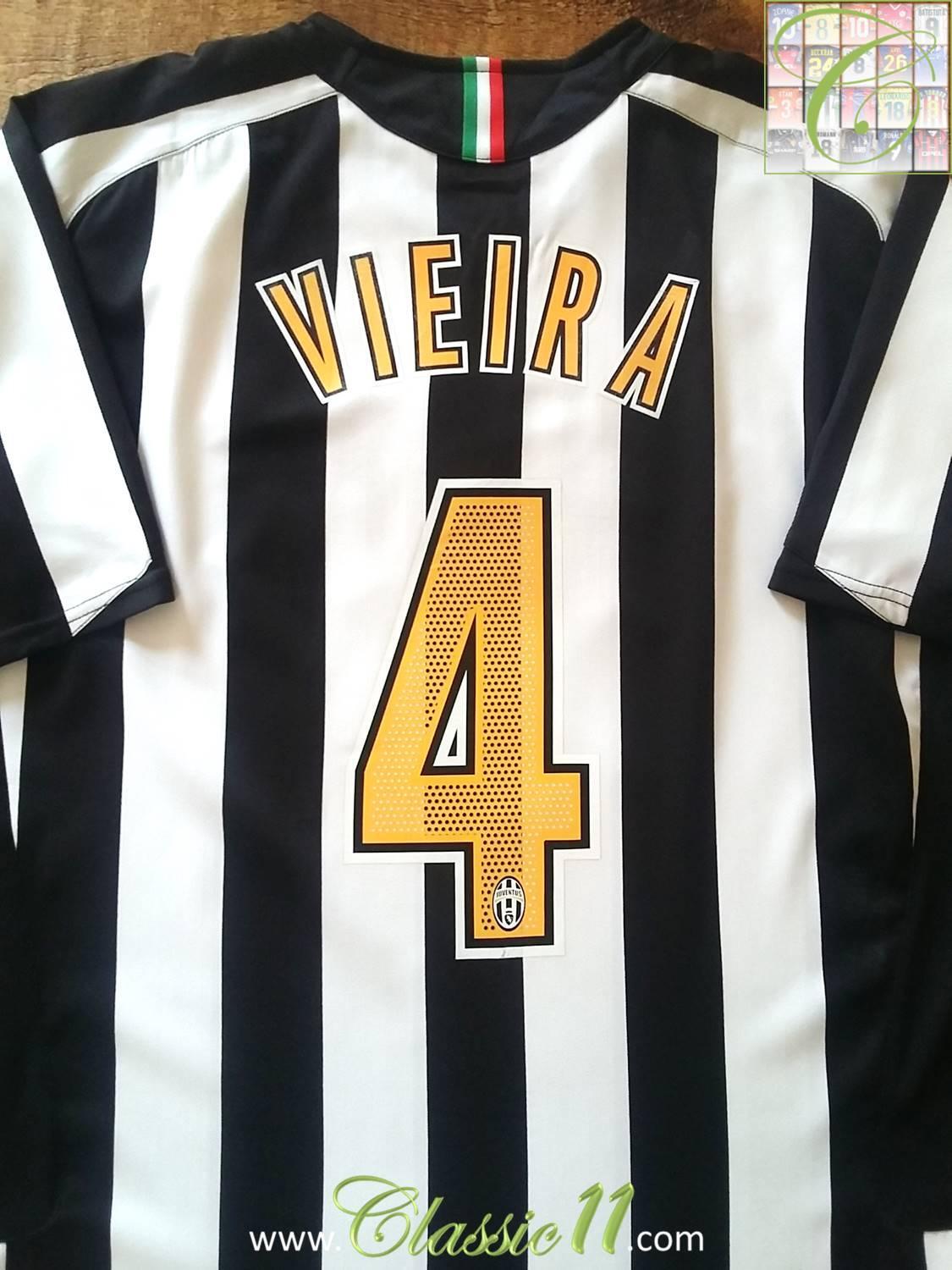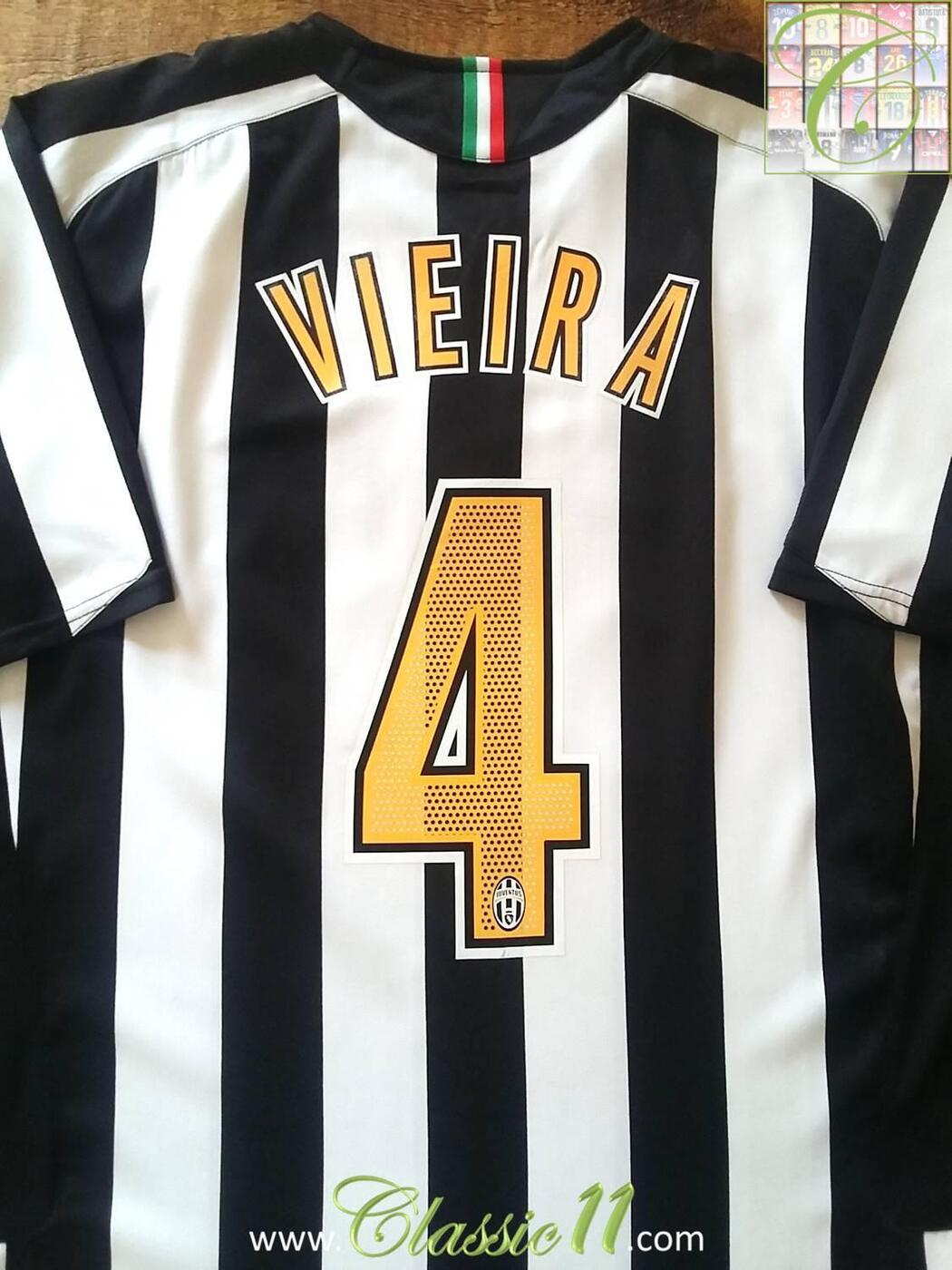
Schriftart Juventus Turin Saison 2005/2006
Kann mir jemand helfen und sagen welche Schriftart hier genutzt wird ? Es handelt sich um das Trikot von Juventus Turin aus der Saison 05/06 von Nike.
Diese Trikot-Schriften sind fast immer Spezialanfertigungen und gerade nicht über einen Produktnamen verfüg- bzw. erwerbbar. Sie sollen ja Original-Shirts verkaufen.
Es gibt dann aber doch meist recht schnell »Fan-Fonts«, die im Internet kursieren. Da deren Legalität aber meist fraglich ist, würde ich hier nichts entsprechendes verlinken wollen.
Gegen einen Nachbau spricht eigentlich nichts, idR sind die ja nicht mal identisch mit der Vorlage. Bei diesem  Beispiel ist das A ohne die hochgezogene Ecke: